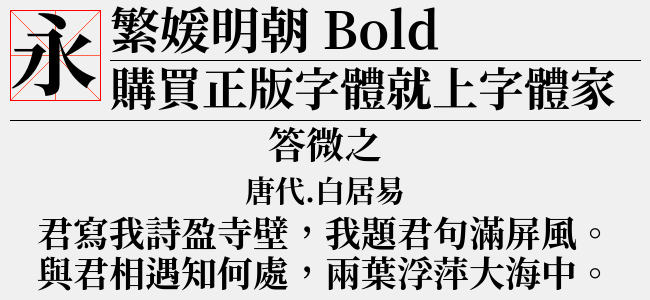
繁媛明朝 TW Bold-佚名
繁媛明朝 TW Bold是一款大小6.44 M的佚名字体,主要特征是印刷,明体,公文,免费商用,繁媛免费商用,,繁媛明朝 TW Bold为TTF格式的文件,采用安装嵌入,包含了符号拉丁文日文中文,字宽中等(正常),当前版本是Version 1.000,共计6763个汉字以及附加其他英文字体和阿拉伯数字。